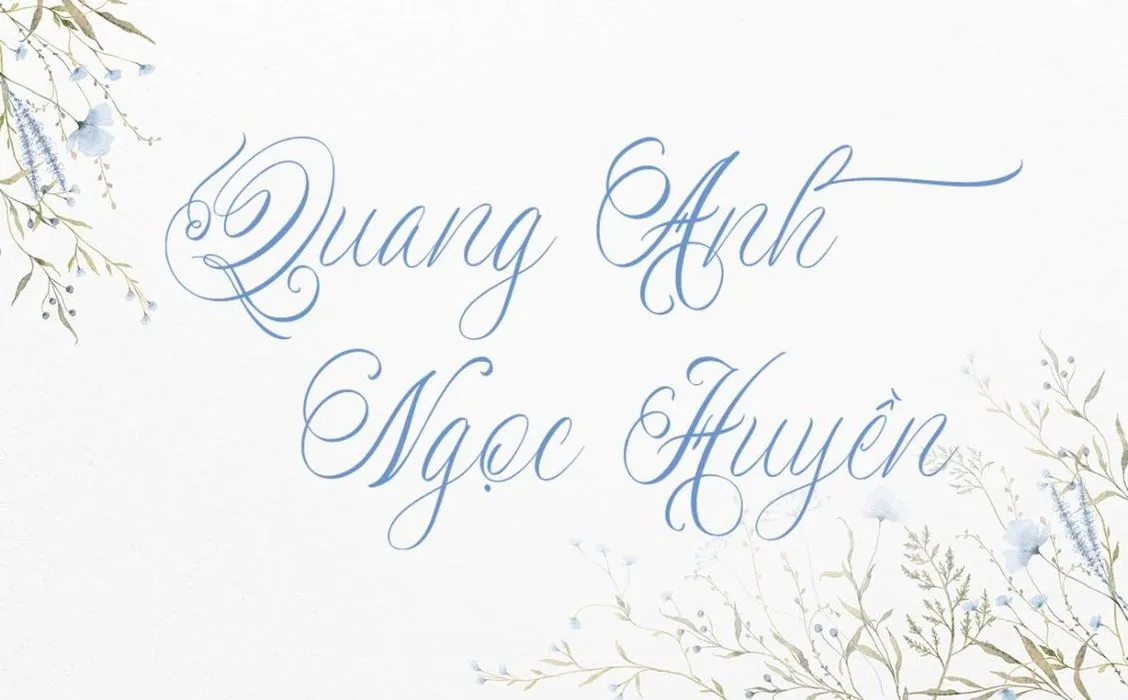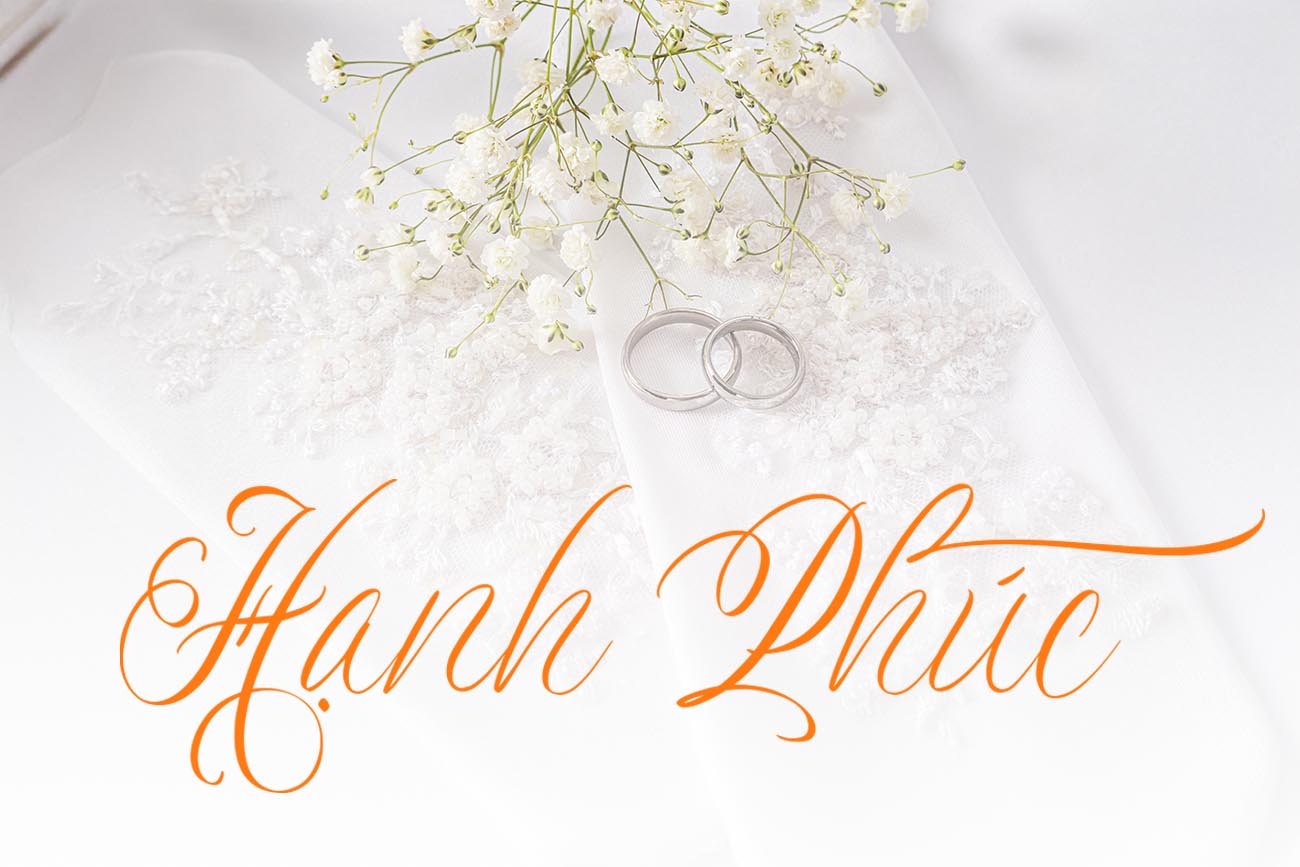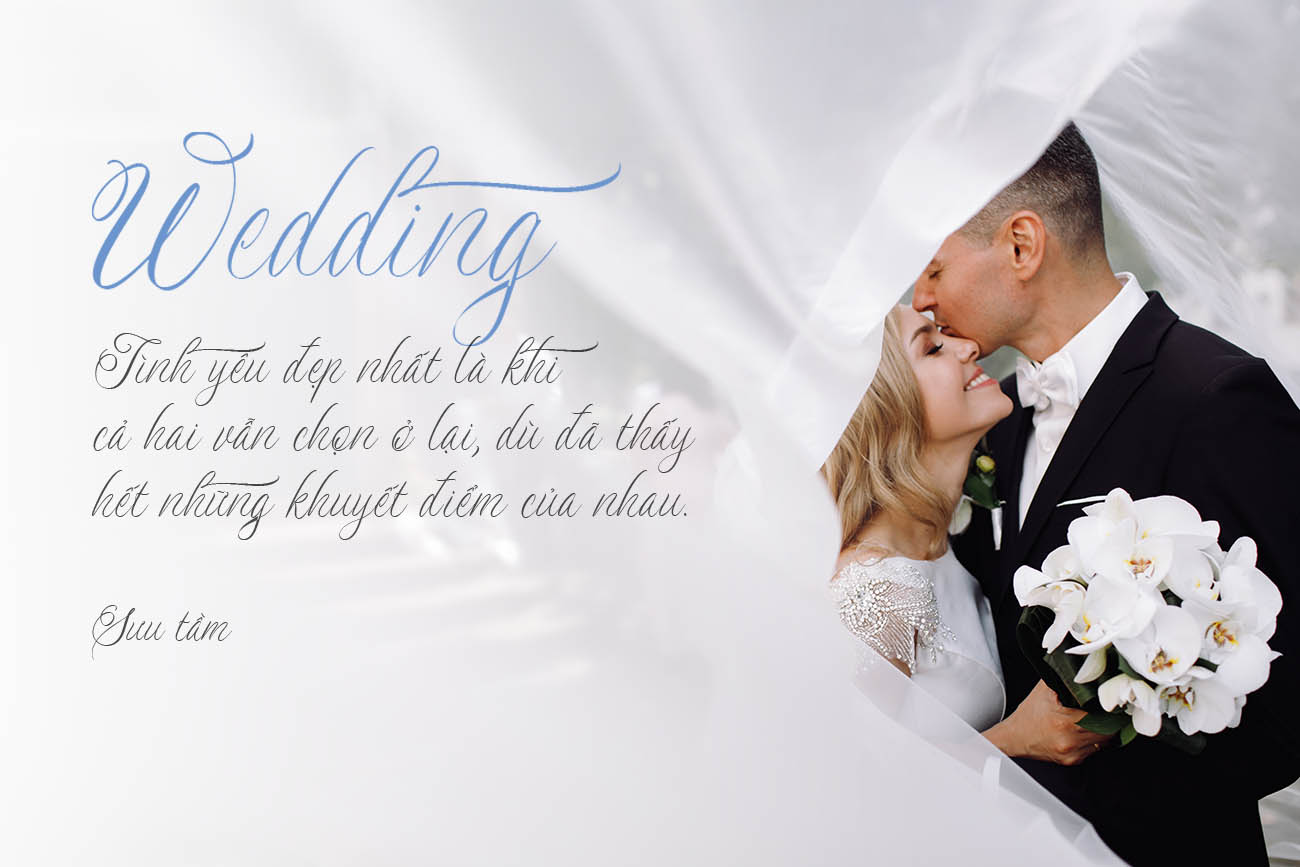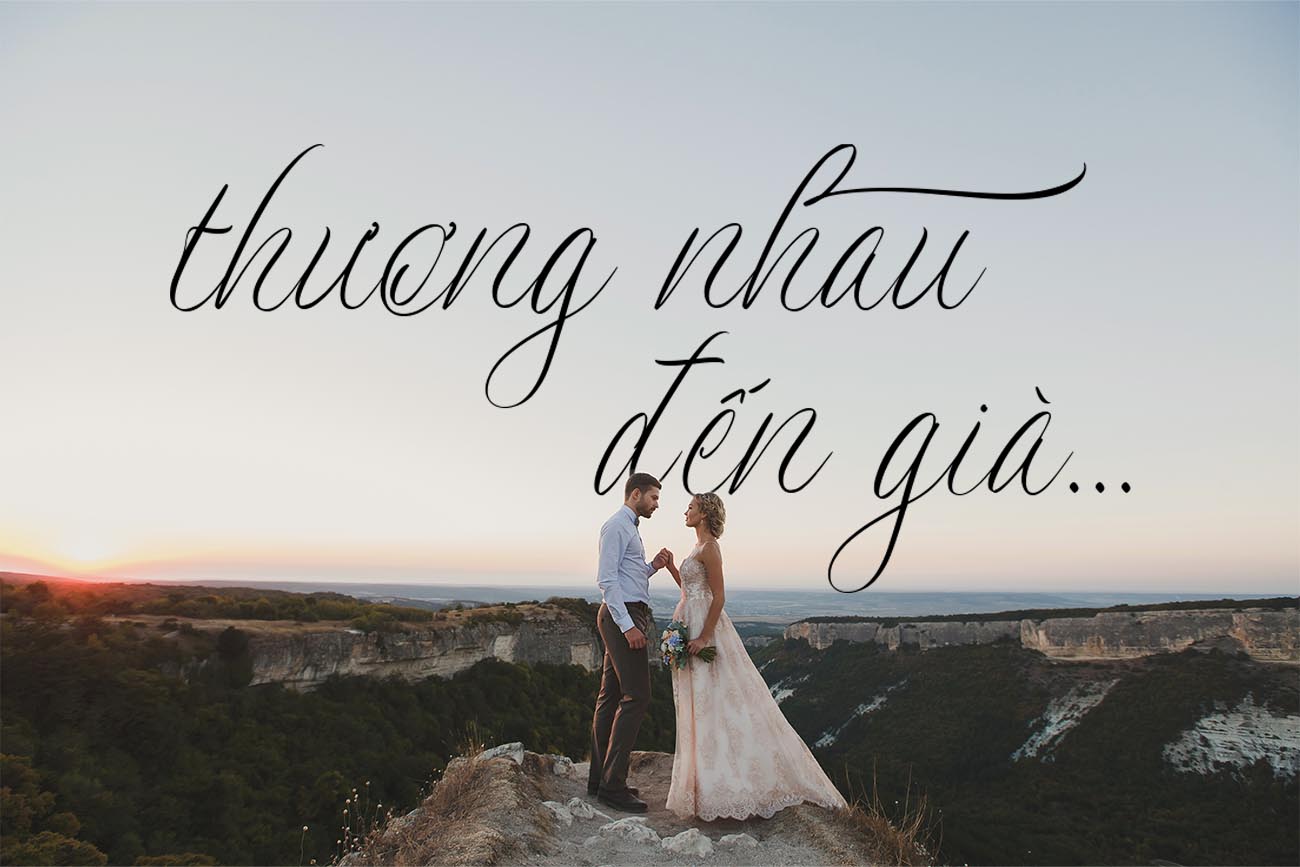
Không chỉ đơn thuần là một công cụ hiển thị văn bản, TH Newly Bridal Việt hóa hiện lên như một tác phẩm nghệ thuật thư pháp kỹ thuật số đầy lôi cuốn. Mang đặc trưng của dòng font chữ viết tay hiện đại, bộ phông này sở hữu những đường nét thanh mảnh, tự nhiên nhưng không kém phần phóng khoáng, mở ra không gian ngập tràn cảm xúc lãng mạn.
Vũ điệu thư pháp hiện đại: Điểm nhấn tạo nên sức hút độc bản của bộ font chính là sự kết hợp hài hòa giữa các ký tự. Các nét nối (ligatures) được vuốt mềm mại, tạo cảm giác như nét chữ được viết trực tiếp bằng mực trên giấy lụa.
Xóa bỏ sự cứng nhắc: Cấu trúc uốn lượn đầy nghệ thuật kết hợp cùng các đường nét bay bổng giúp phá vỡ sự rập khuôn của phông chữ máy tính thông thường, đem đến cái hồn tự nhiên, sống động cho tác phẩm.
Sự lựa chọn hoàn hảo cho mùa cưới: Với bản Việt hóa chỉn chu, từng dấu câu tiếng Việt được tinh chỉnh hài hòa, biến TH Newly Bridal thành "vũ khí" lý tưởng để thiết kế thiệp cưới, bảng chào mừng, hay các dự án branding cao cấp, lãng mạn.